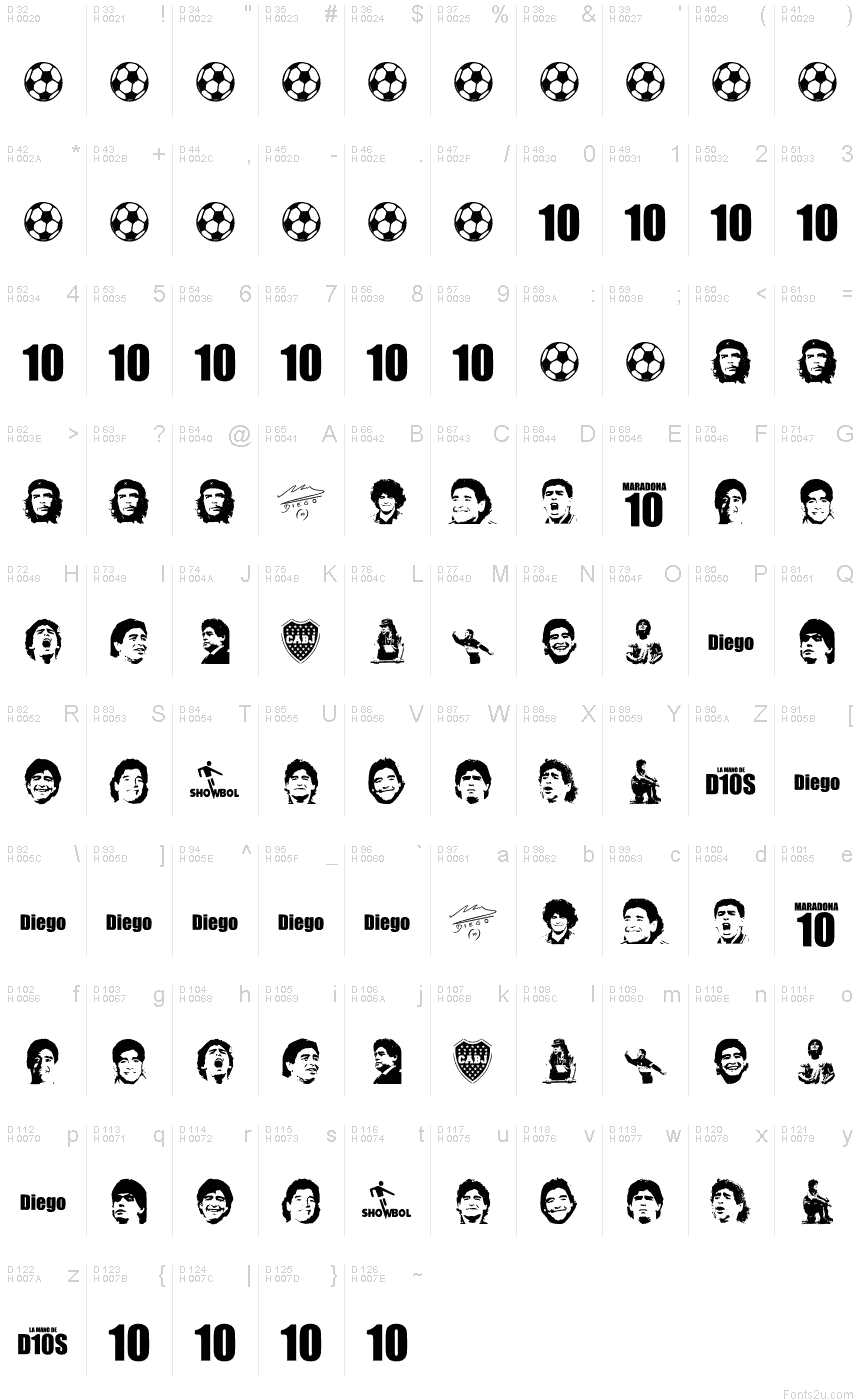
grande maradona
ESTA TIPOGRAFIA DINGBAT ESTA DEDICADA AL MAXIMO IDOLO DE TODO LOS TIEMPOS DEL FUTBOL MUNDIAL!!!!
ESE ES DIEGO ARMANDO MARADONA!!!!
Y TAMBIEN DEDICADO A TODO EL PUEBLO DE ARGENTINA!!!